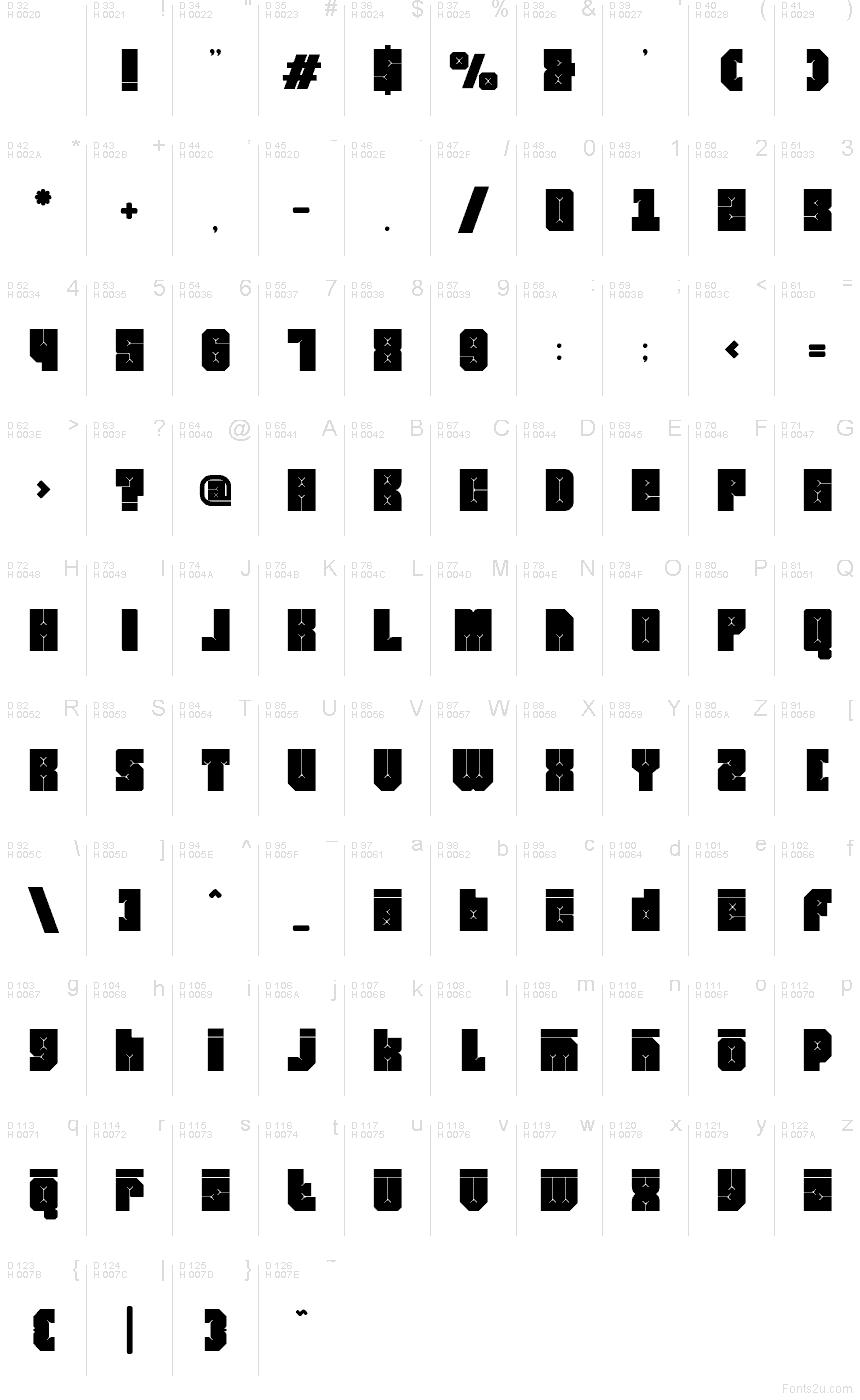
Friez One od Putracetol Studio je bezplatné písmo typu display, které utváří architektonický, vlysovitý rytmus vysokých vertikálních bloků, tenkých příček a zkosených rohů. Opakující se vidlicovité konce a úzké členění panelů dodávají písmenům vyřezávaný, modulární charakter, který působí spíše dekorativně než čistě geometricky.
Díky tomu je silnou volbou pro plakáty, obaly alb, nadpisy akcí, obaly produktů a titulky, kde písmena potřebují fungovat stejně jako vzorovaná plocha i jako nositel významu. Krátké brandingové linky a grafika obálek obzvláště těží z těchto větvených konců, které vytvářejí výrazný okrajový efekt, místo aby působily jako běžné bezpatkové písmo.